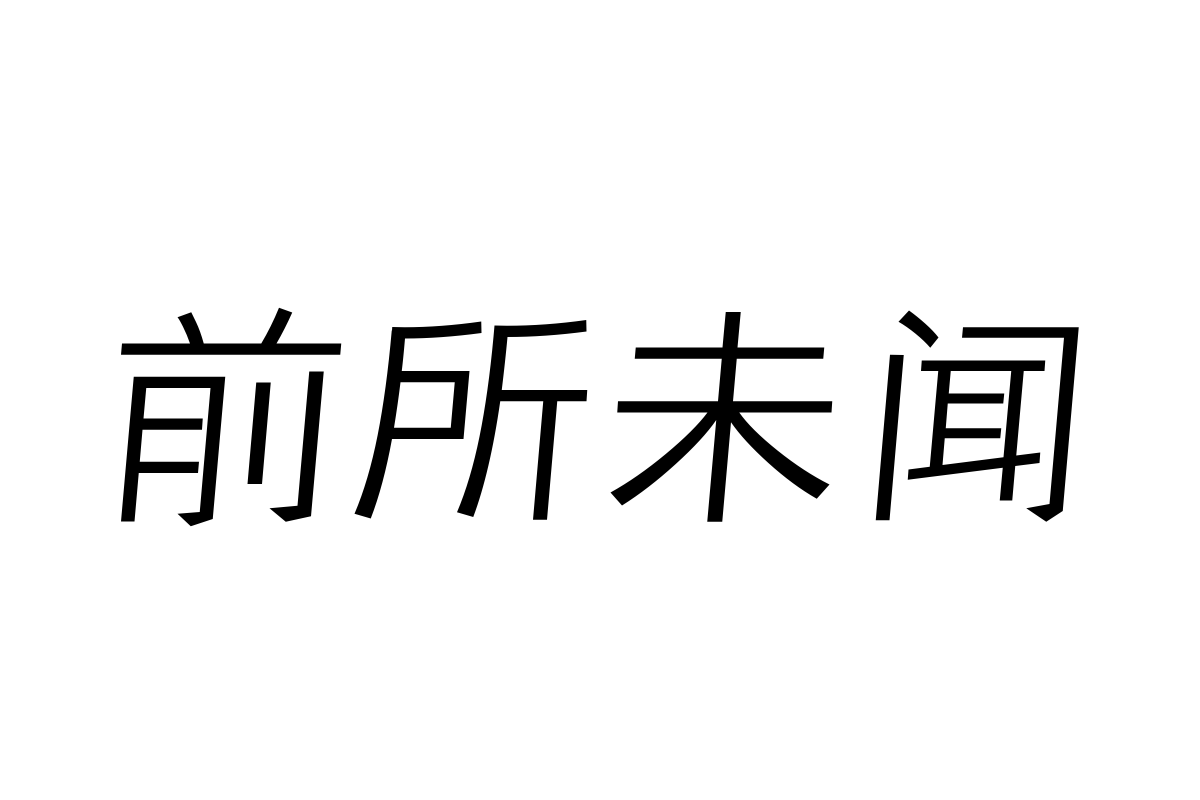
三极铿锵体纤细是一种字体,它的设计灵感来源于汉字的书法艺术。这种字体的特点是线条流畅、结构紧凑,给人一种优雅而有力的感觉。
在三极铿锵体纤细中,每个字的笔画都经过了精心的设计和调整,使得整个字体既有力度又有美感。这种字体适合用于各种需要展示文字美感的场景,如书籍封面、海报、广告等。
三极铿锵体纤细的特点包括:
1. 线条流畅:每个笔画都经过精心设计,使得整个字体看起来流畅自然。
2. 结构紧凑:虽然笔画流畅,但每个字的结构都非常紧凑,不会显得拥挤。
3. 优雅有力:这种字体既有优雅的线条,又有有力的结构,给人一种优雅而有力的感觉。
4. 易于识别:由于笔画流畅且结构紧凑,所以这种字体非常易于识别。
总之,三极铿锵体纤细是一种非常适合用于展示文字美感的字体,无论是用于书籍封面、海报还是广告,都能给人留下深刻的印象。